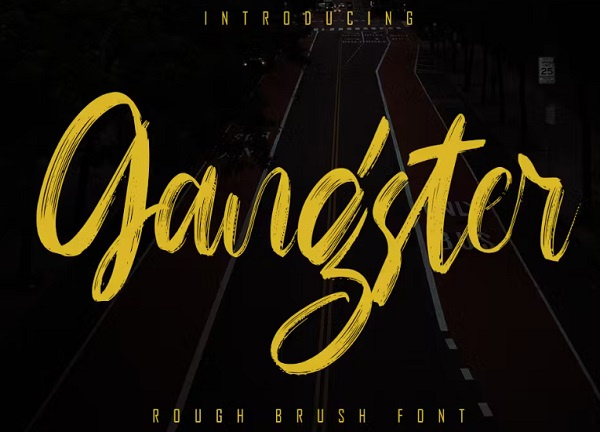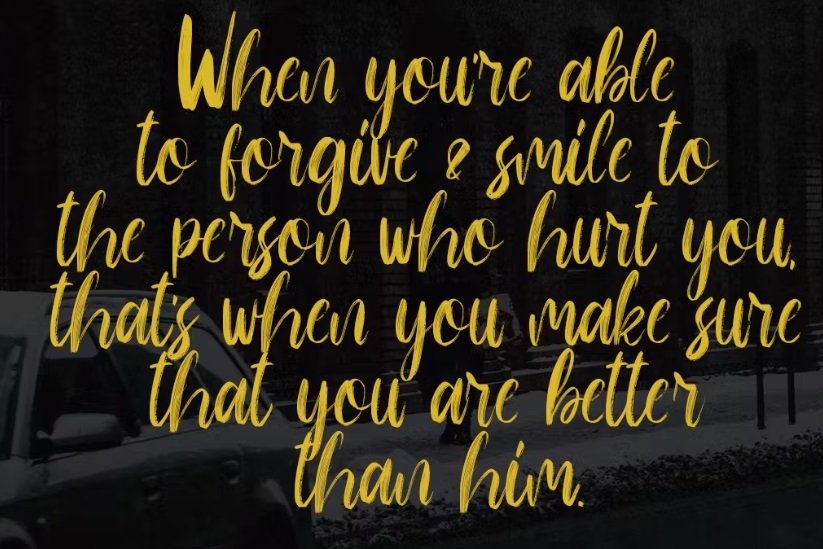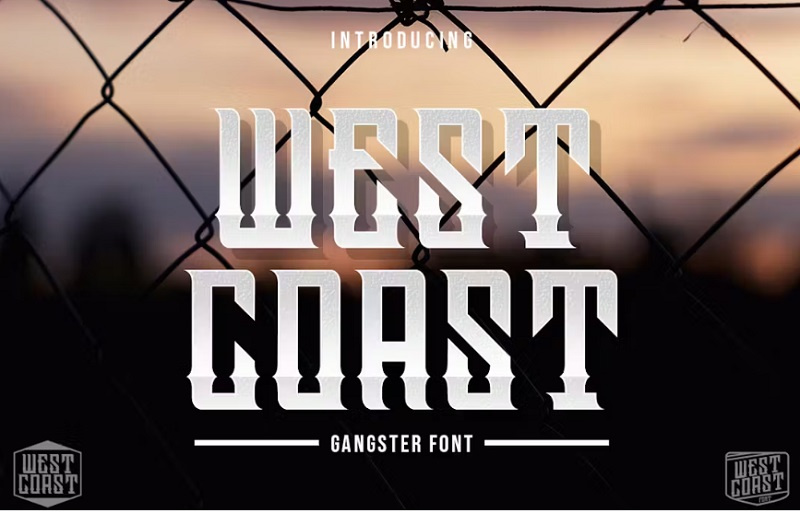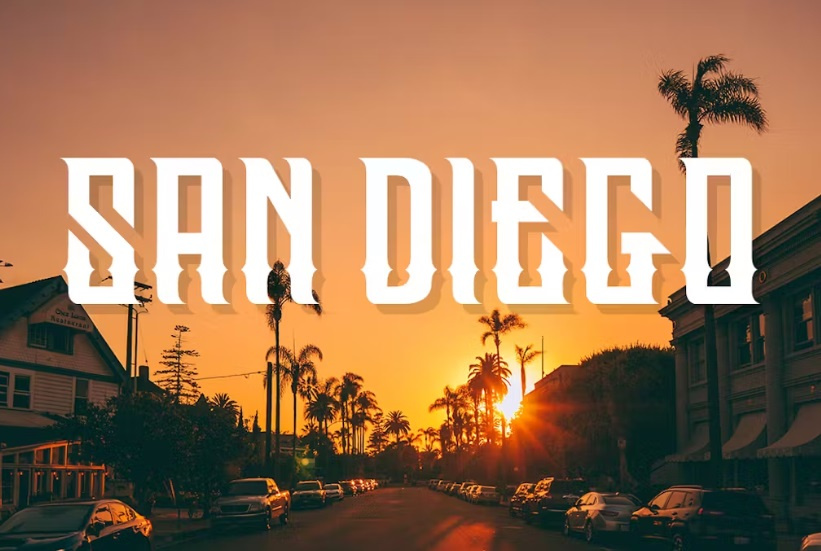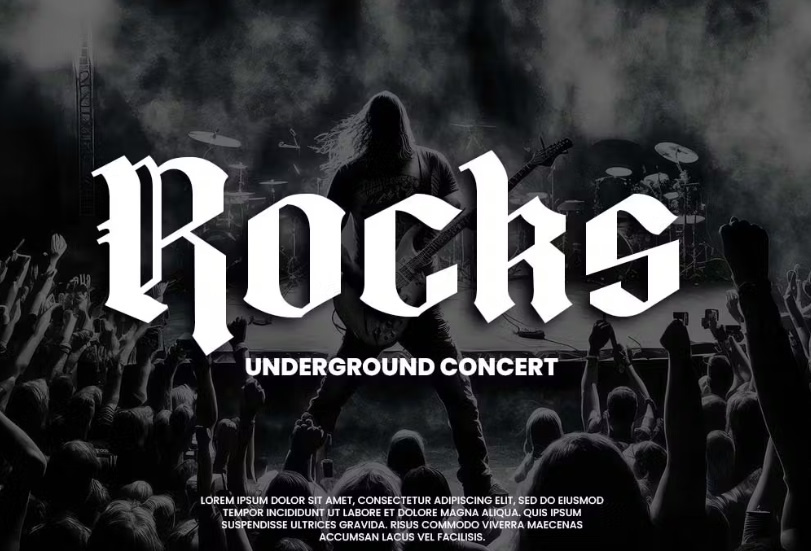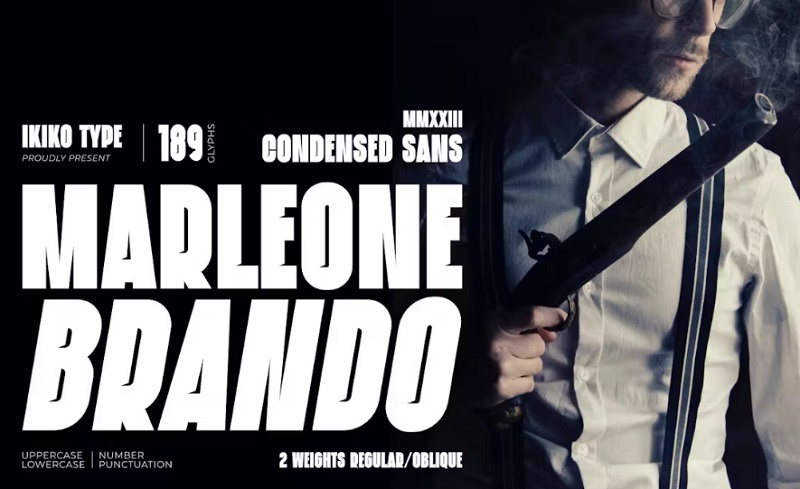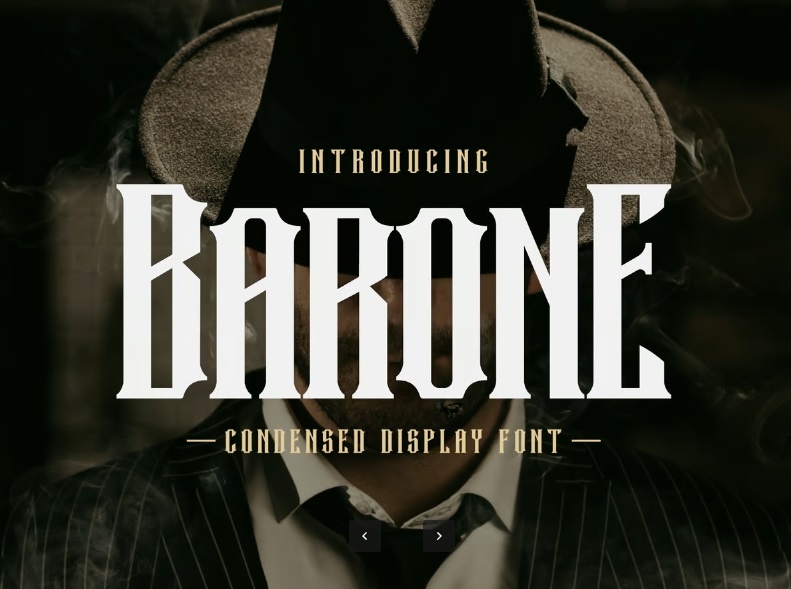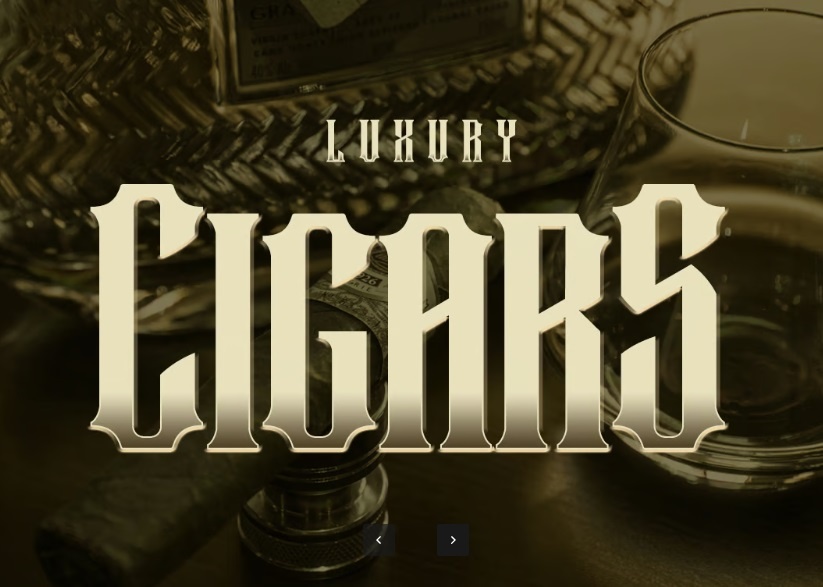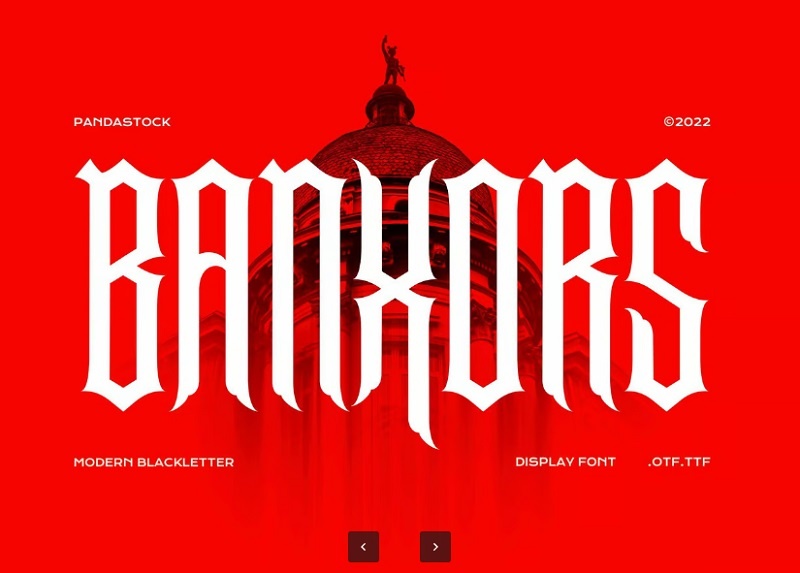
فونت انگلیسی گنگستر از جی اف ایکس دانلود. شامل 6 فونت انگلیسی به سبک گنگستری می باشد. از این فونت بسیار کاربردی می توانید در طراحی های گرافیکی، تبیلغاتی، صفحه آرایی بروشور، کاتالوگ، پوستر، طراحی خالکوبی، تاتو، لوگو، بسته بندی و ... استفاده کنید. برای مشاهده پیش نمایش این مجموعه فونت زیبا در ادامه مطلب با ما همراه باشید.
فونت گنگستری انگلیسی با نام Barone ایده آل برای پوسترها ، برند تجاری، و طراحی ها که با تم قدیمی هستند می باشد. این فونتها اغلب برای القای حس قدرت، خطرناکی، عصیانگری و سبک زندگی خیابانی مورد استفاده قرار میگیرند.
فونت گنگستر انگلیسی Banxors
فونت انگلیسی گنگستر Banxors با سبک بلک متال یک فونت با حروف تیز و زاویهدار است. مناسب برای جلد آلبوم، پوستر، فونت های لوگو، دعوت نامه ها و دیگر طرح هایی که به دنبال طراحی پر قدرت و متال هستند.